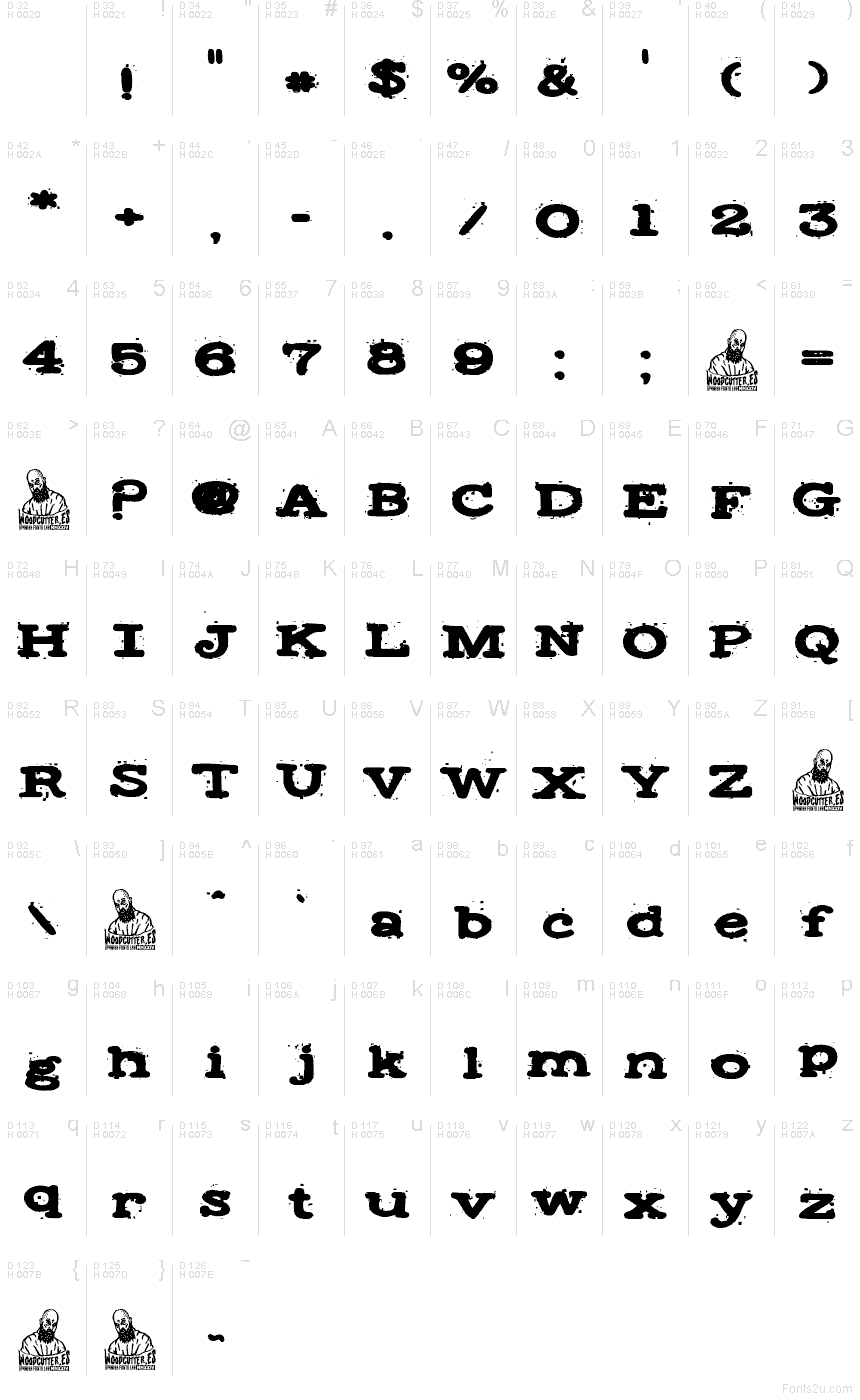
Type Brutus
Písmo Type Brutus od Woodcutter Manero je bezplatný distressed font typu display s mohutnými tvarmi a drsnými, otlačenými okrajmi. Znaky nesú roztrúsené škvrny od atramentu a vysekané časti, ktoré dodávajú celému písmu textúru opotrebovanej ručnej tlače bez toho, aby stratilo svoju pevnú a masívnu štruktúru.
Type Brutus skvele funguje v nadpisoch plagátov, obaloch albumov, letákoch k akciám, hernej grafike či odvážnych reklamných predmetoch, pretože poškodené hrany pôsobia ako zámerný dizajnový prvok, nie ako vizuálny šum. Toto bezplatné písmo sa hodí aj pre logá, texty na bannery a obaly, ktoré vyžadujú efekt hrubej pečiatky so silným grafickým charakterom.